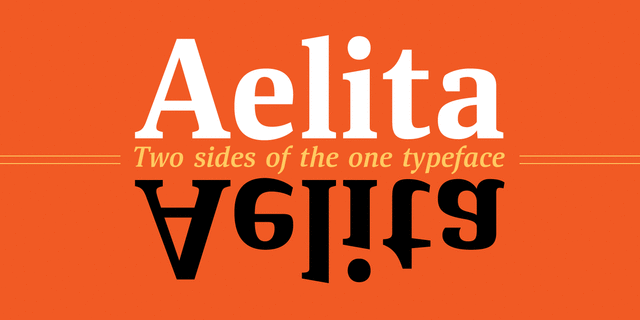
Aelita — малоконтрастная антиква в 6 начертаниях. Характерная особенность шрифта — альтернативный набор строчных знаков, в значительной мере изменяющий рисунок текста. Основной комплект знаков — достаточно строгий, с геометрически четким рисунком капель и жестким примыканием овалов к вертикальным штрихам; альтернативный — более свободный, с несколько более каллиграфическим характером. Нейтральный рисунок основного варианта знаков позволяет использовать шрифт при работе и с научно-популярными, и с художественными текстами. Использование стилистических альтернатив уместно в фантастике, фэнтези, книгах по искусству. Шрифт разработан дизайнером Натальей Васильевой и выпущен компанией ПараТайп в 2014 году.
авторитетный, надежный, стабильный, убедительный, деловой, серьезный, спокойный, твердый, уверенный, простой, строгий, ровный, гармоничный, универсальный, понятный, нейтральный, средний, обычный, уравновешенный, космополитичный, ненавязчивый, умеренный, техничный, современный, точный, логичный, неброский, практичный, оптимальный, доступный, статичный, культурный, образованный, устойчивый, гуманитарный, городской, умный, вежливый, интеллигентный, сильный, мотивирующий, ответственный